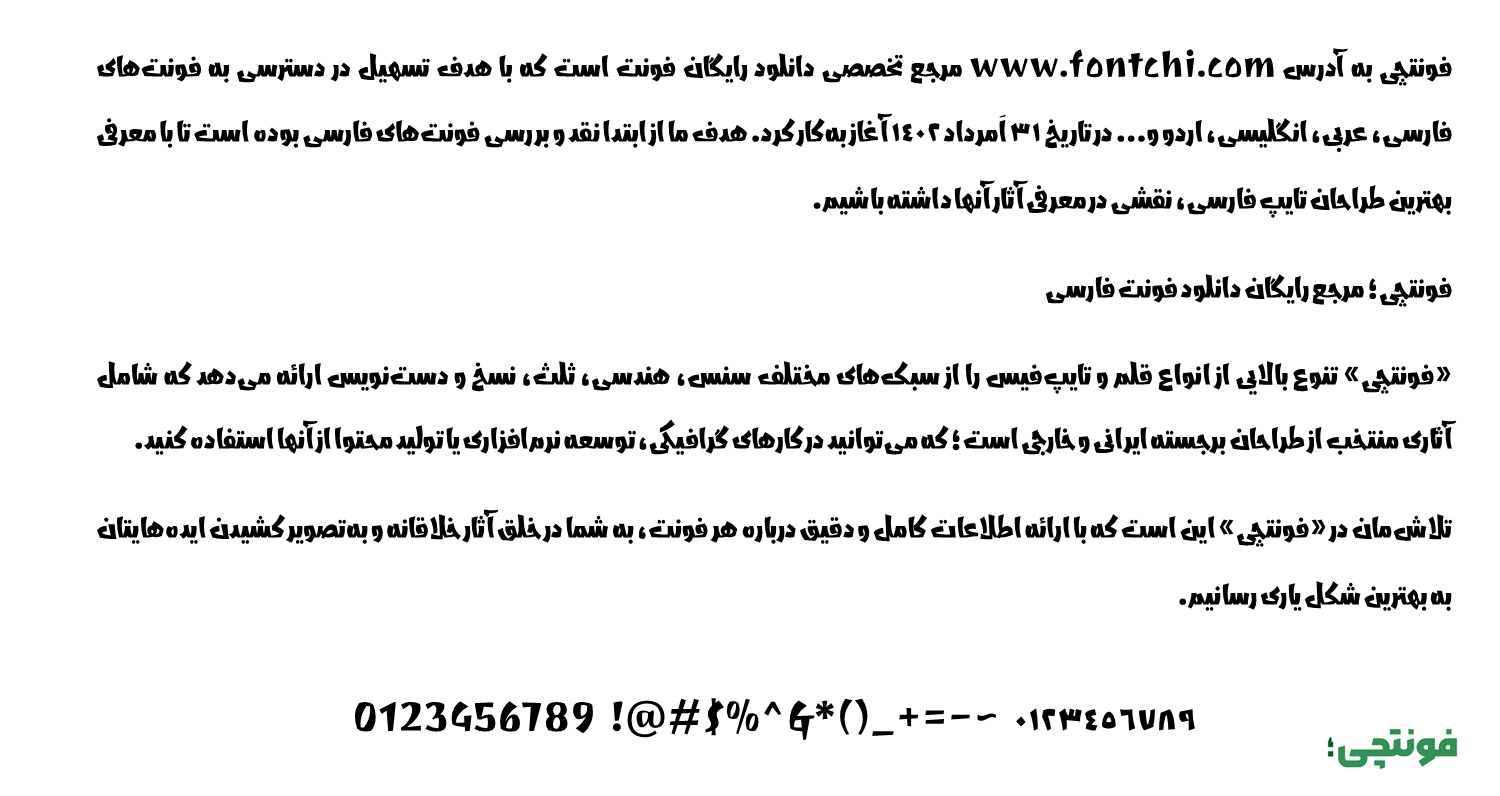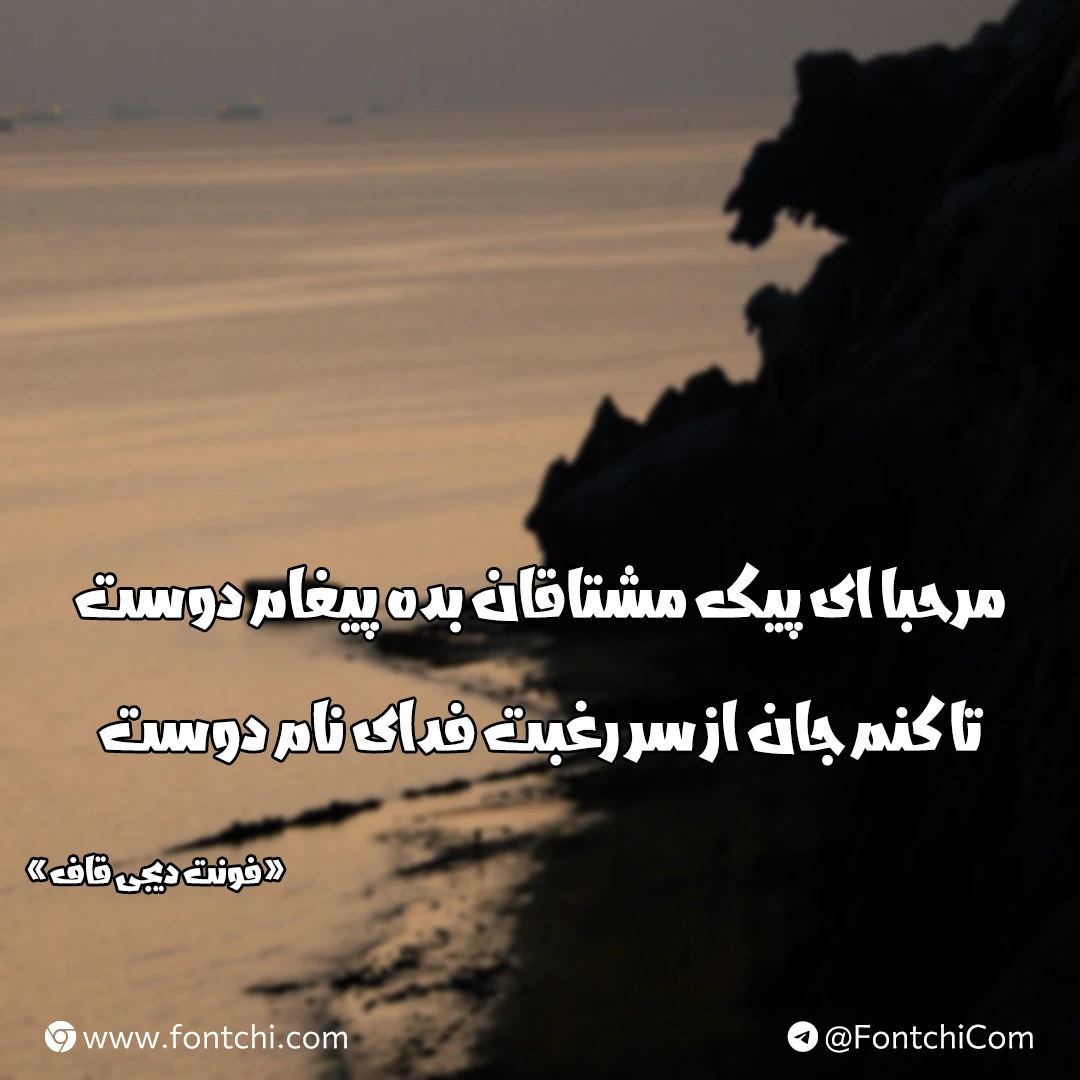
فونت دیجی قاف (Digi Ghaf)
فونت دیجی قاف (به انگلیسی: Digi Ghaf) یک فونت نمایشی، هندسی و فانتزی است که توسط گروه دیجی فونت بازطراحی شده است. این فونت بر اساس یک فونت دموی عربی به نام ابدو توسعه یافته و برای استفاده در زبانهای فارسی و کردی بهینهسازی شده است. تغییرات اعمالشده شامل اصلاح ساختار حروف، افزودن کاراکترهای زبان کردی و ارائه جایگزینهای متنوع برای حروف است.
ظاهر فونت دیجی قاف بولد است و دارای یک نسخه وزنی Bold است که از زبانهای انگلیسی و عربی نیز پشتیبانی میکند. ظاهر این فونت فانتزی به شکلی است که میتوانید از آن برای عناوین در پروژههای نمایشی مثل پست کاور و تامنیل ویدئوهای شبکههای اجتماعی یا فونت متون کوتاه تبلیغاتی استفاده کنید.
بررسی و دانلود فونت دیجی قاف (Digi Ghaf) سبک فانتزی
دیجی قاف با ساختاری هندسی و خطوط ضخیم طراحی شده که ظاهری جسور و چشمگیر به آن بخشیده است. این فونت به دلیل وزن سنگین و فرمهای هندسی، برای جلب توجه مخاطب در عناوین و شعارهای تبلیغاتی بسیار مناسب است.
حروف با زوایای تیز و خطوط مستقیم طراحی شدهاند که حس مدرنیته و قدرت را منتقل میکنند. وزن بولد فونت دیجی قاف در پسزمینههای شلوغ خوانایی و برجستگی را به خوبی حفظ میکند. پشتیبانی از برخی حروف و جایگزینهای فانتزی برای زبان کردی نیز آن را به انتخاب ایدهآل برای کارهای نمایشی تبدیل کرده است.
فونت digi ghaf به دلیل ویژگیهای فانتزی خود برای پروژههایی از جمله موارد زیر کاربردی است:
- عناوین و تیترها: برای پوسترها، بنرها، جلد کتاب و تبلیغات.
- عکسنوشتهها: در شبکههای اجتماعی مانند اینستاگرام برای استوریها و پستهای گرافیکی.
- طراحی لوگوتایپ: به دلیل شخصیت قوی، میتواند در طراحی لوگوهای خلاقانه استفاده شود.
- پروژههای فانتزی و عاشقانه: ساختار هندسی و پویای فونت، آن را برای طراحیهای رمانتیک و کمدی نیز مناسب میکند.
این فونت فارسی با وزن سنگین و فرمهای هندسی خود ظاهری دارد که موجب جلب توجه میشود. فاصلهگذاری استاندارد بین حروف با کرنینگ متعادل نیز خوانایی آن را در اندازههای بزرگ فوقالعاده کرده است. اما در مقابل این فونت ضخیم برای استفاده در متون خیلی بلند مناسب نیست.
فونت دیجی قاف؛ زیر تیغ مقایسه
از سری فونتهایی با این سبک فانتزی میتوان به فونت پتک و والهالا اشاره کرد. با اینکه از نظر هندسی و ظاهری این ۳ فونت مشابه هم نیستند، اما ساختار فانتزی آنها ره به گزینههایی مناسب برای متون تبدیل کرده است.
فونت پتک یک فونت مدرن و مینیمال است که برای طراحیهای ساده و حرفهای مناسب است. این فونت اغلب در دسته فونتهای sans-serif قرار میگیرد و برای رابطهای کاربری، وبسایتها و متون چاپی استفاده میشود.
در این فونت سادگی خطوط بدون زوائد اضافی، پشتیبانی از چند وزن متنوع، خوانایی بالا در اندازههای کوچک و بزرگ رعایت شده است. برای استفاده در سایتها و اپلیکیشنها، کارهای گرافیکی مینیمال و مدرن یا متون تبلیغاتی با ظاهر جذاب مناسب است.
در حالی که فونت دیجی قاف با محدودیتهای وزنی و ساختاری با سطح فانتزی بالاتر، بیشتر برای کارهای دم دستی مناسب است و روی جلب توجه تمرکز دارد که میتواند برای کارهای تبلیغاتی یا شبکههای اجتماعی مناسب باشد.
فونت والهالا نیز دارای ظاهری نمایشی با الهام از سبکهای فانتزی و حماسی است. این فونت به دلیل فرمهای تزئینی و الهامگرفته از اساطیر (مانند اساطیر نوردیک) برای پروژههای خاص و خلاقانه طراحی شده است.
وجود فرمهای تزئینی و پیچیده با جزئیات زیاد، وزن سنگین و ظاهر حماسی آن را به انتخاب مناسبی برای عناوین و طرحهای فانتزی بدل کرده است. از این فونت میتوانید در پوسترهای فیلم و بازیهای ویدیویی، طراحی لوگوهای فانتزی یا پروژههای گرافیکی با تم اساطیری استفاده کنید.
در حالی که فونت دیجی قاف با ظاهری مدرن و امروزی دارای کاربردهای معاصر است. اما والهالا برای استفاده در پروژههای حماسی و کلاسیک کاربردیتر است.